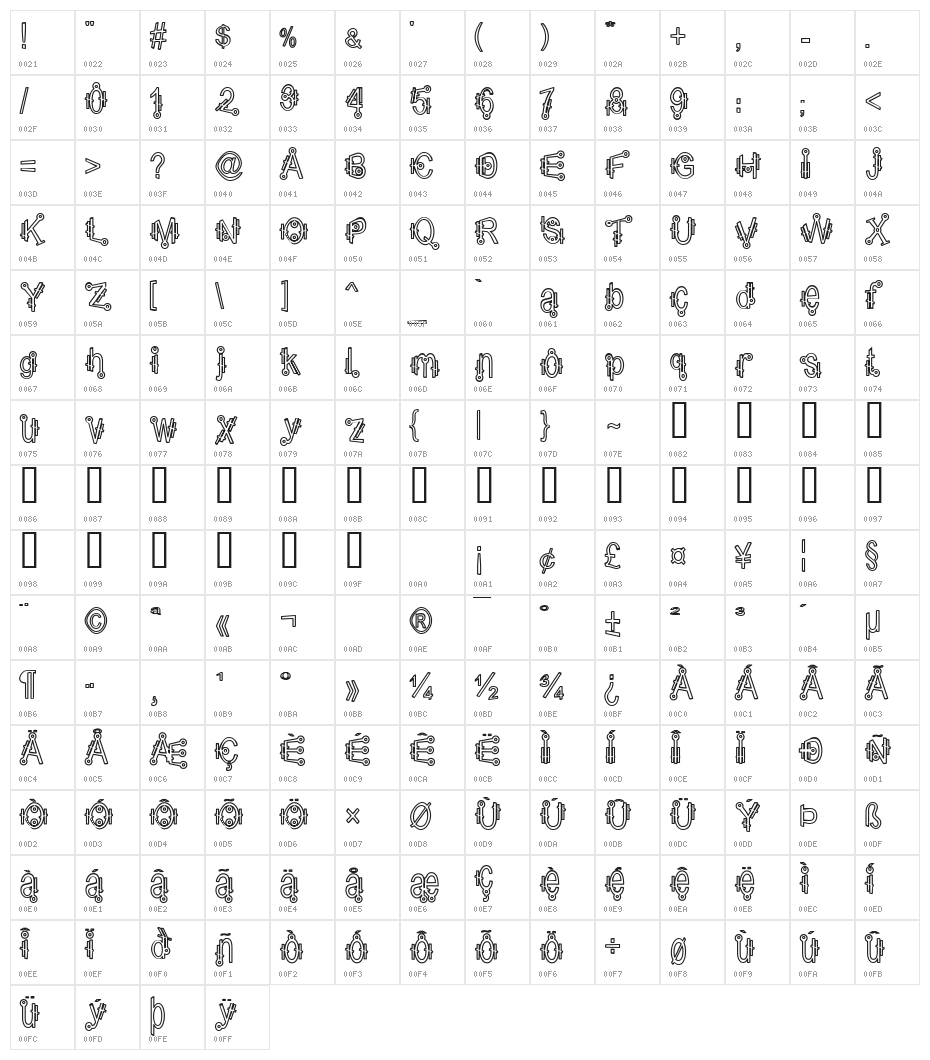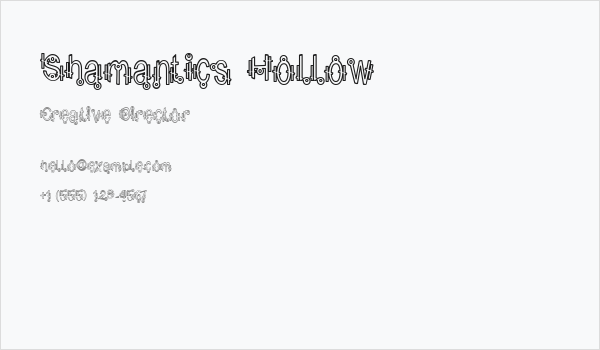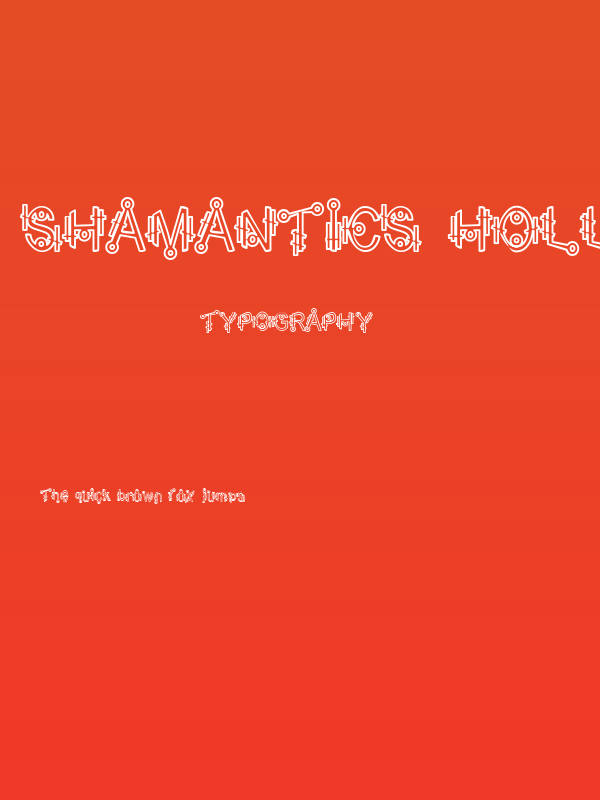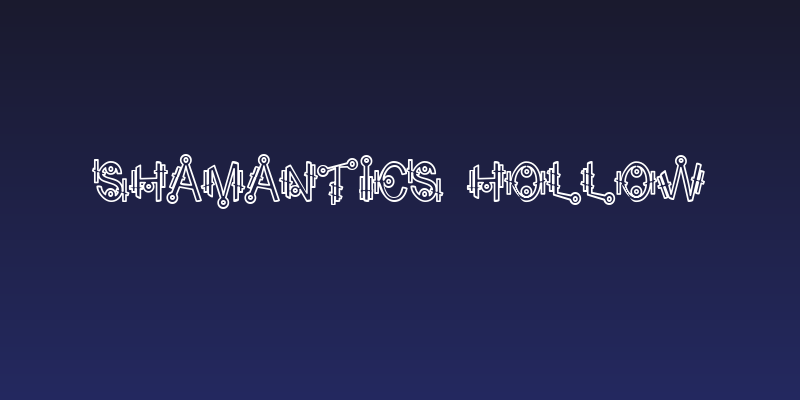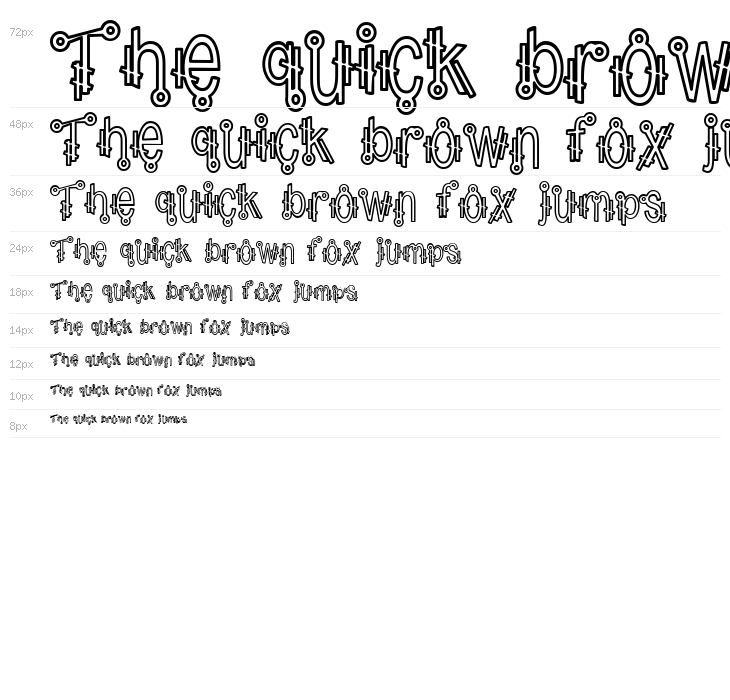
Shamantics Hollow Font
| Stile generale | Futuristic, Playful, Mechanical |
| Progetti proposti | Ideal for creative projects such as posters, album covers, video game graphics, and branding for tech-related products. |